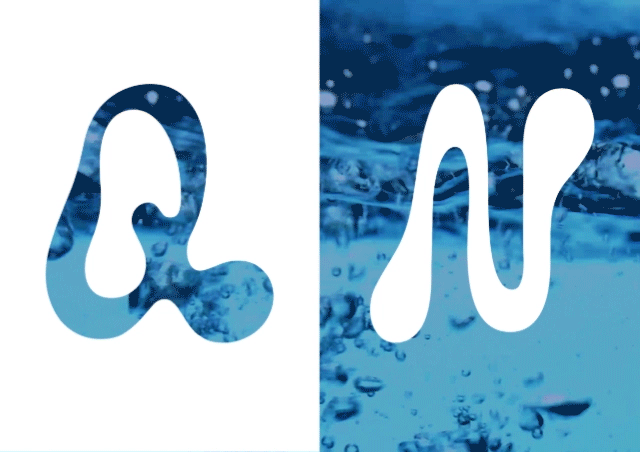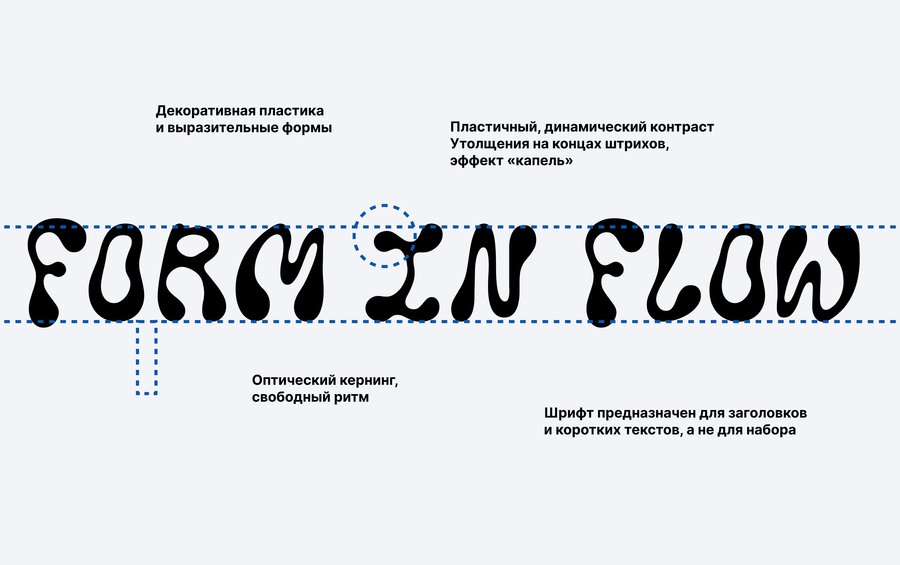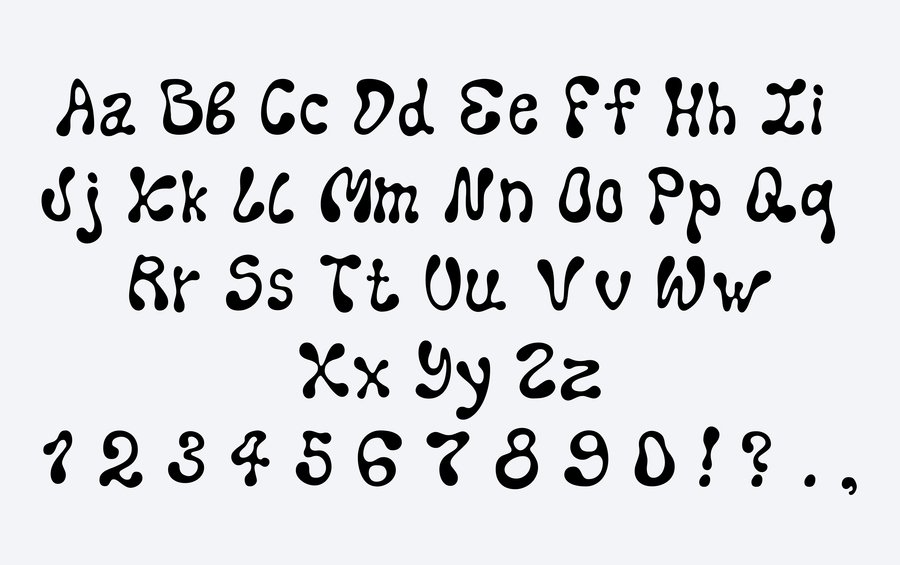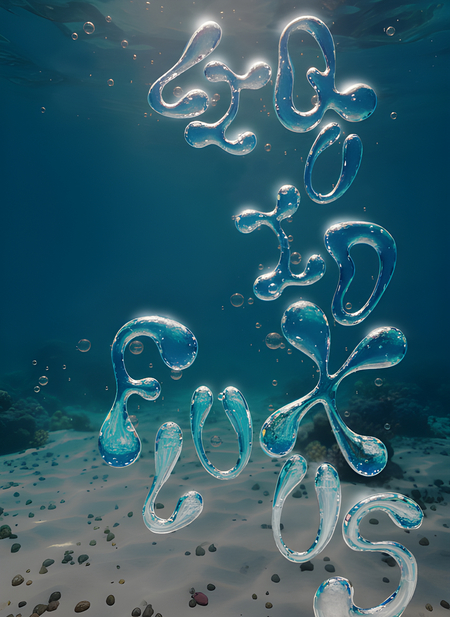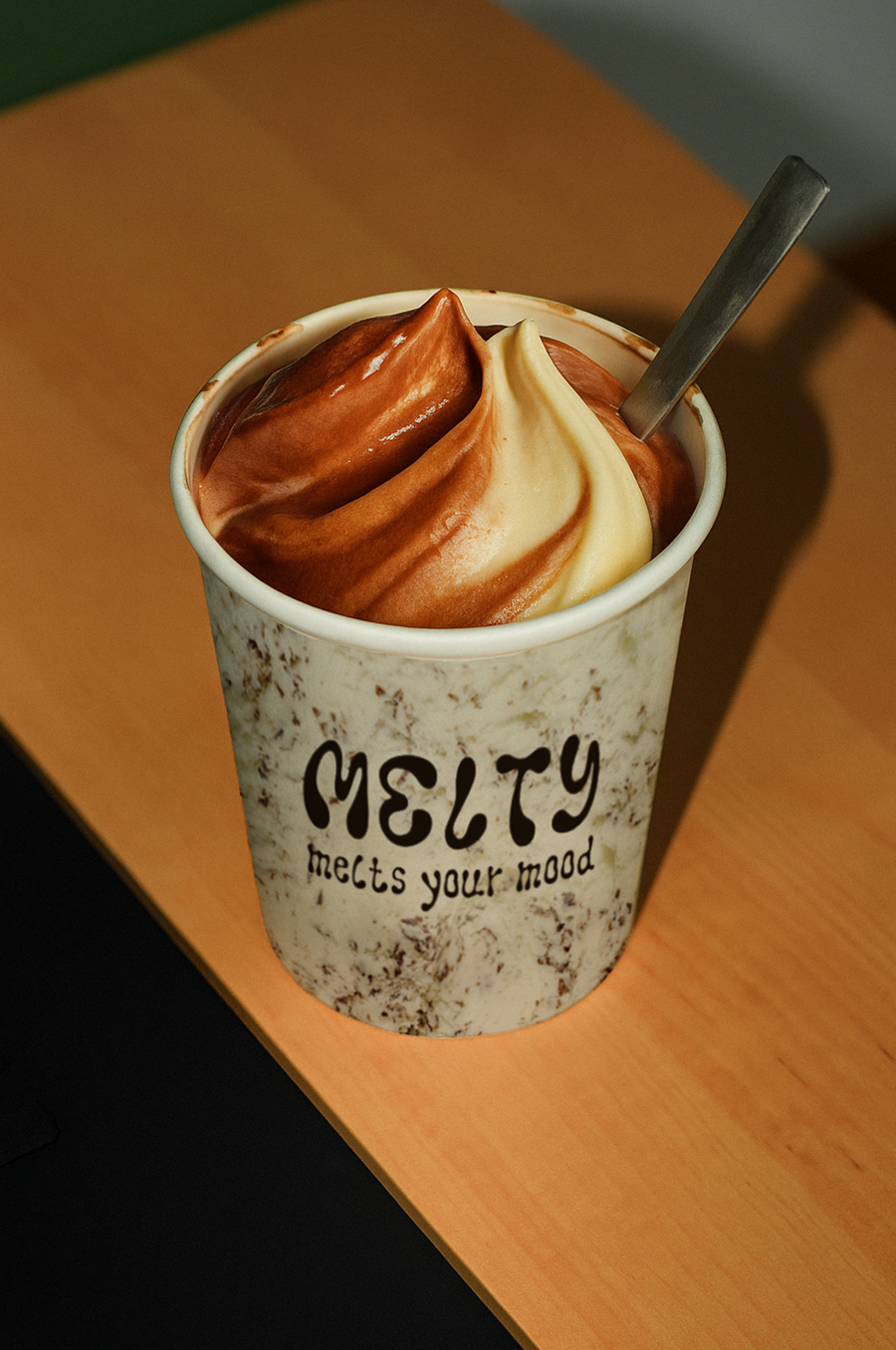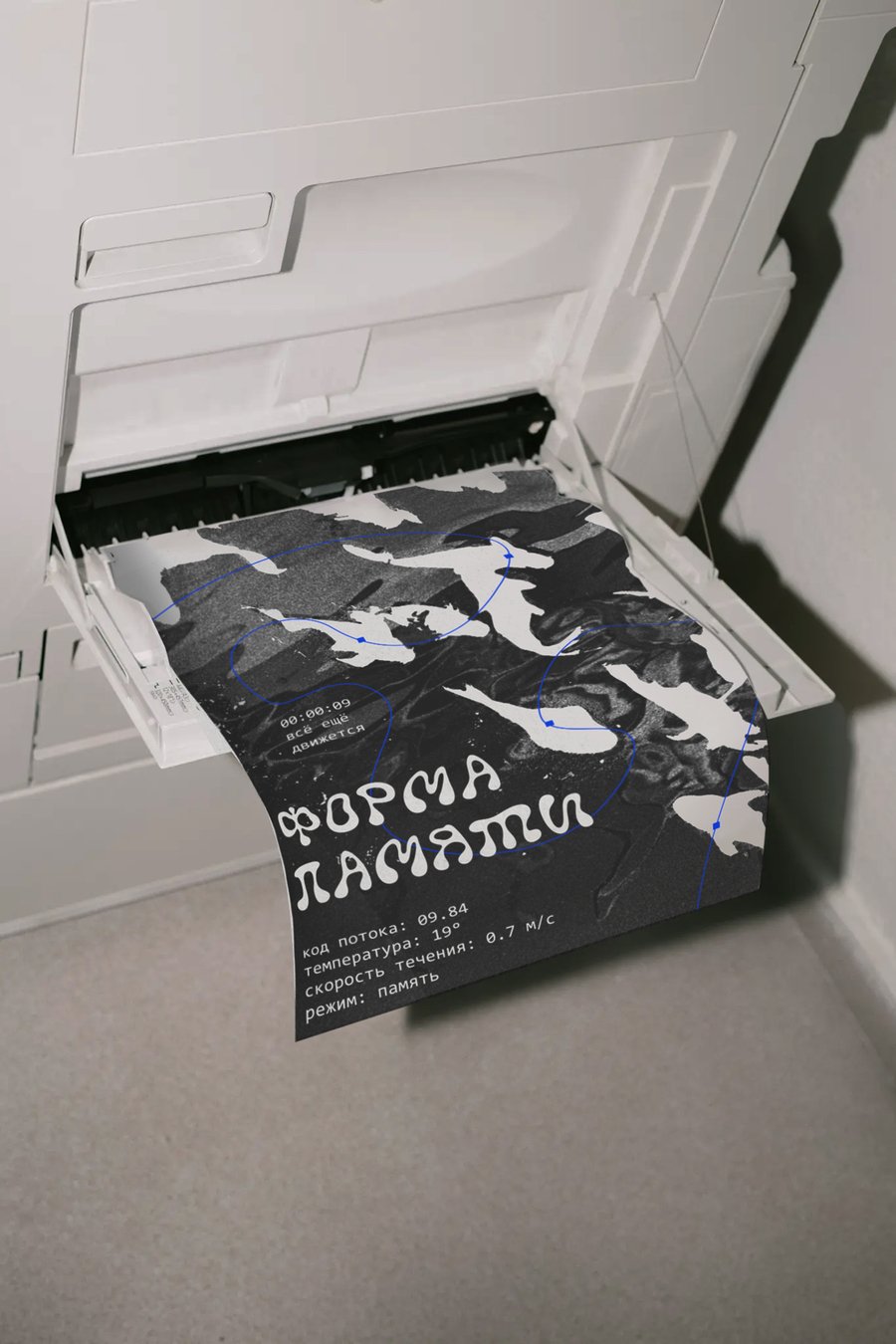
Fluxus — акцидентный шрифт о текучести и живой форме. Он рождается из движения — пластичные линии и мягкие переходы создают ощущение непрерывного потока, в котором форма будто дышит и изменяется. Этот шрифт органичен и чувственен — он живёт по своим законам, сопротивляясь геометрии и симметрии. Визуальный ритм, превращающий слово в движение, а текст — в поток.